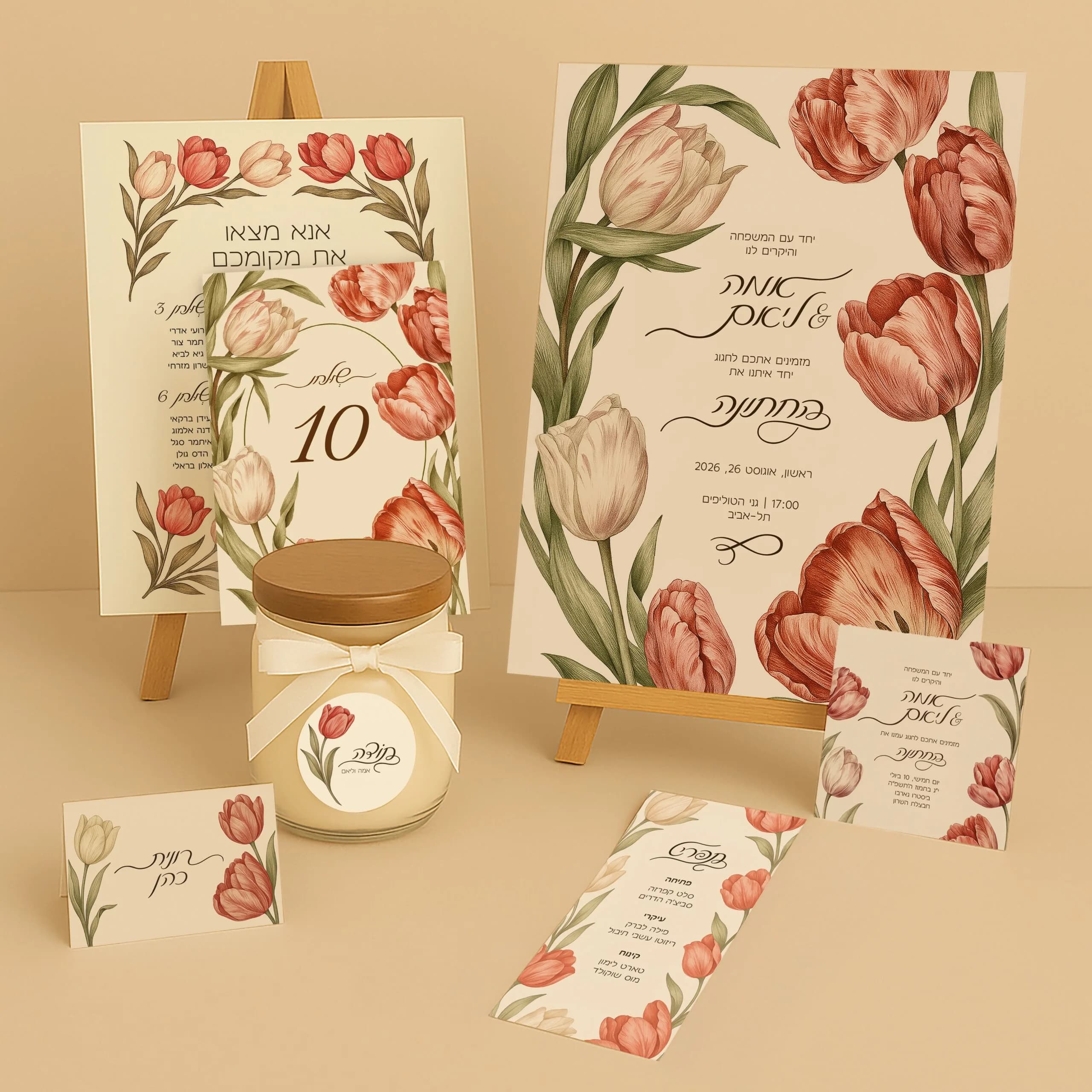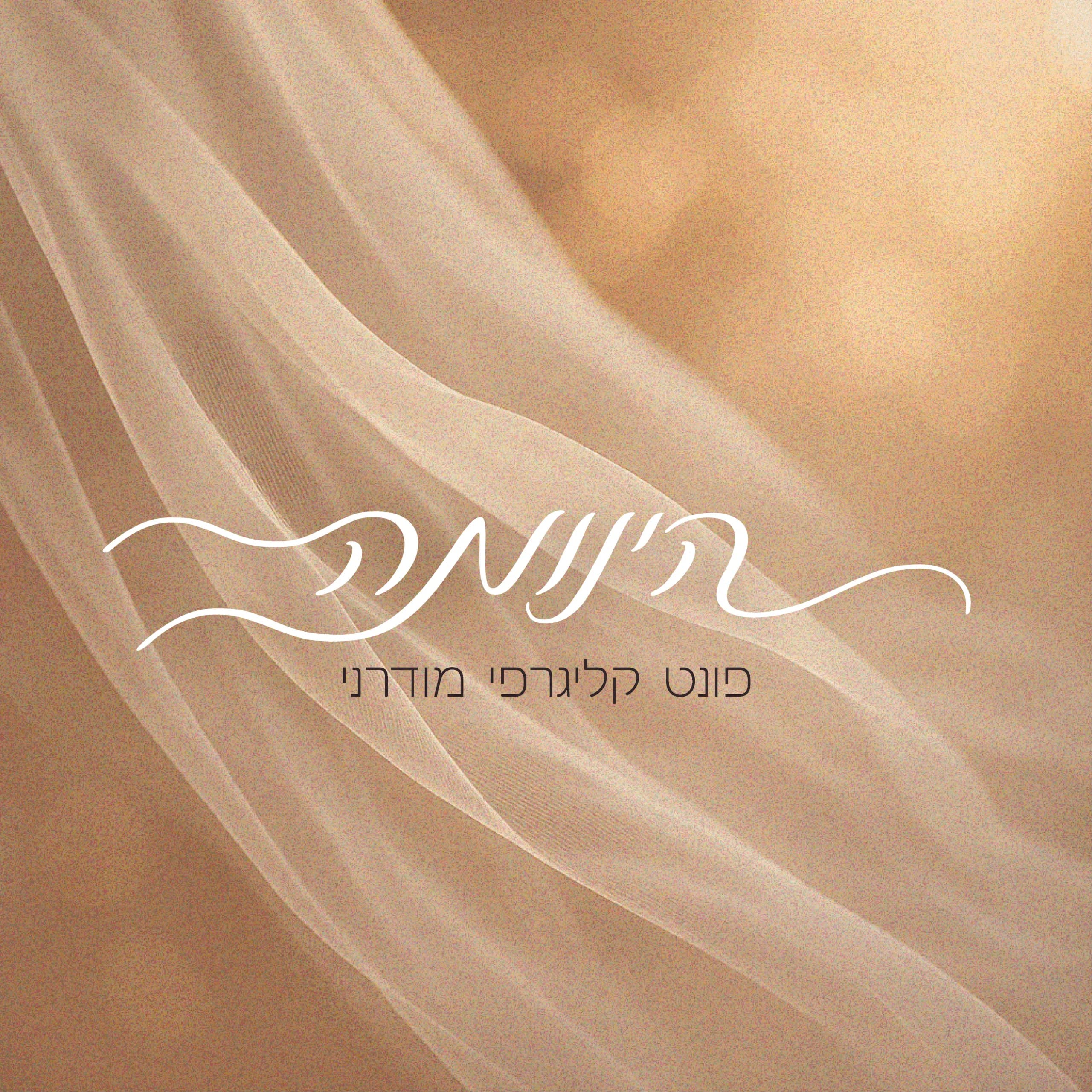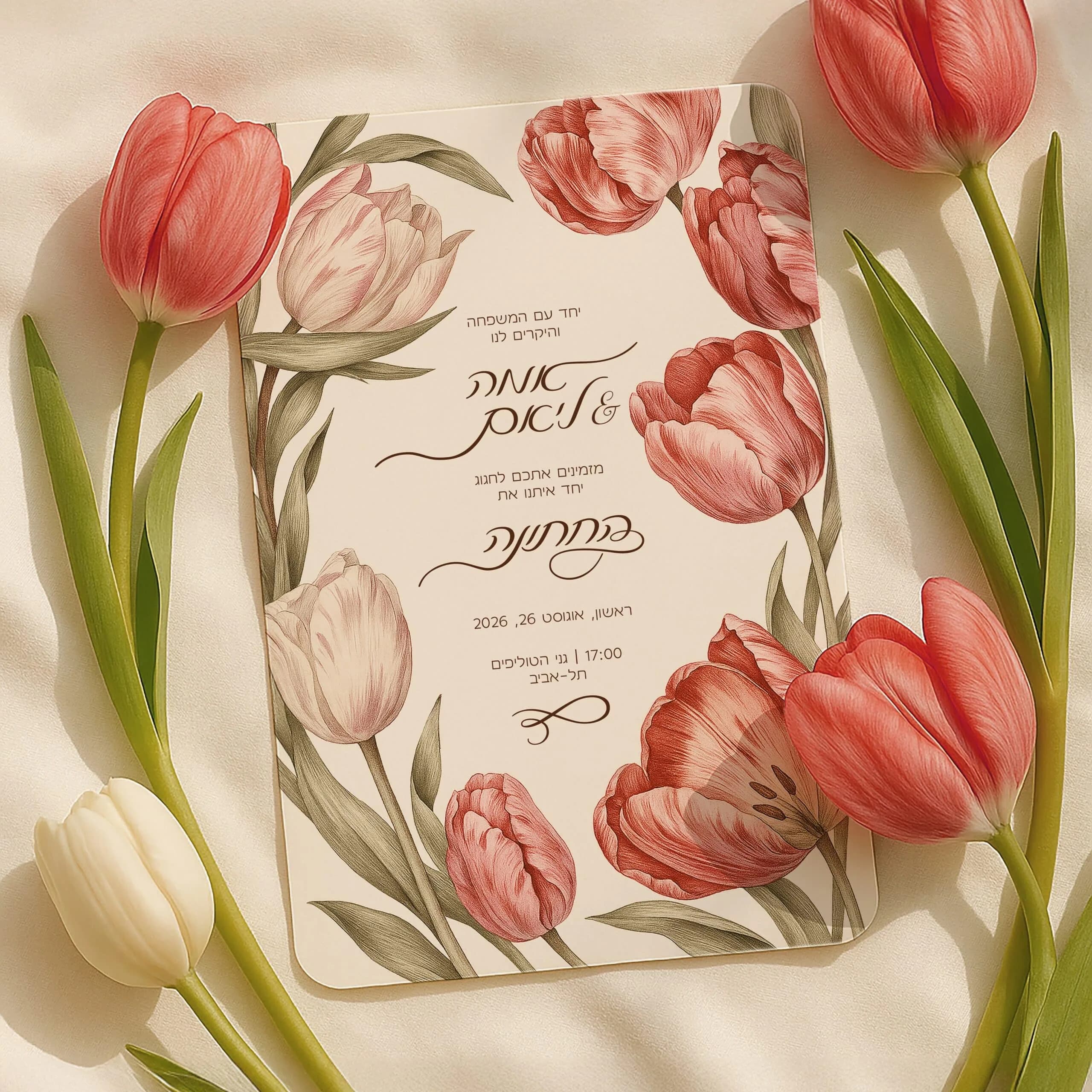
בהשראת רפרוף בד ההינומה והאלגנטיות של טקס החופה, עם נגיעות קליגרפיות עכשוויות ומינימליסטיות, הינומה מעניק איזון מושלם בין רומנטיקה עדינה לטוהר מודרני, מה שהופך אותו לכלי המושלם להזמנות חתונה, מיתוג אירועים יוקרתיים, מגזינים, אתרי לייף-סטייל וחוויות דיגיטליות המבקשות להשאיר רושם. הפונט מגיע בתמיכה מלאה לניקוד. דיוק טיפוגרפי, מרווחים מאוזנים להפליא ופרופורציות הרמוניות שמעניקות שלווה עיצובית. התאמה מושלמת לדיגיטל ולדפוס, אידיאלי לכותרות רגשיות, טקסטים מלאי אופי, וגם לטקסטים ארוכים וקריאים.